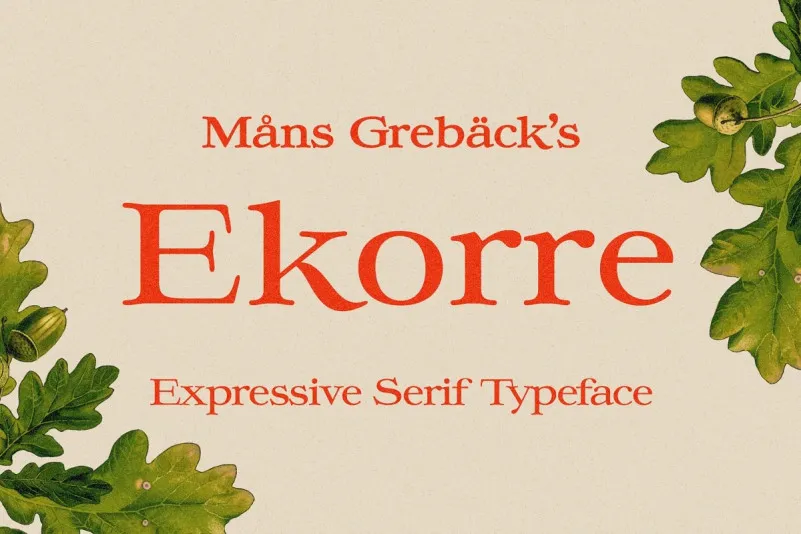
Esta fonte é uma elegante serif vintage com estilo suavemente oxidado. Desenhada e criada por Mans Greback em 2021, a família de fontes criativa apresenta um visual retro vibrante e personalidade forte. Construída com ângulos arredondados e formas fluidas, expressando simpatia enquanto preserva seriedade. A fonte “Ekorre Font” se destaca não apenas por sua aparência vintage, mas também pela capacidade de transformar qualquer projeto em um texto que transmite sentimentos suaves e confiáveis ao mesmo tempo. Seja para aplicativos de design gráfico ou publicações digitais, esta fonte vai adicionar um toque autêntico aos seus projetos, oferecendo uma alternativa única na seção Font Categories da 99designs.